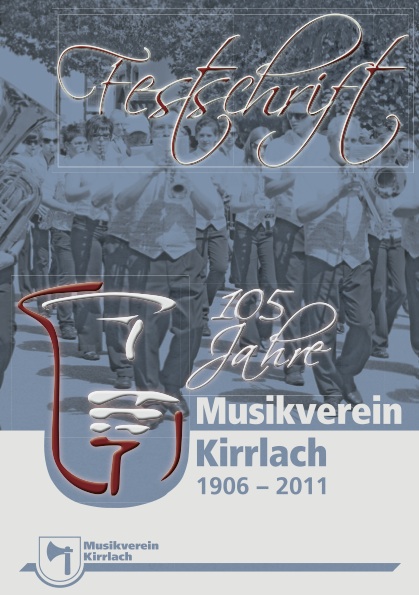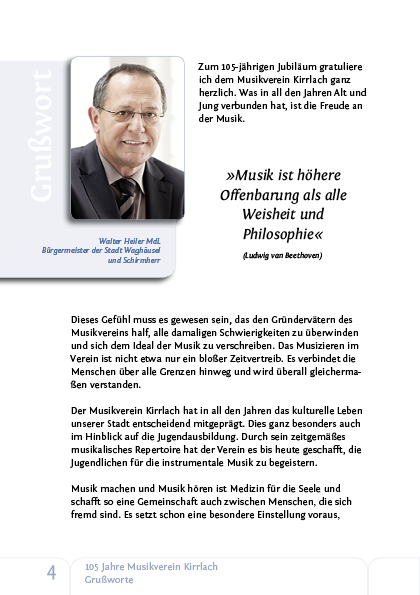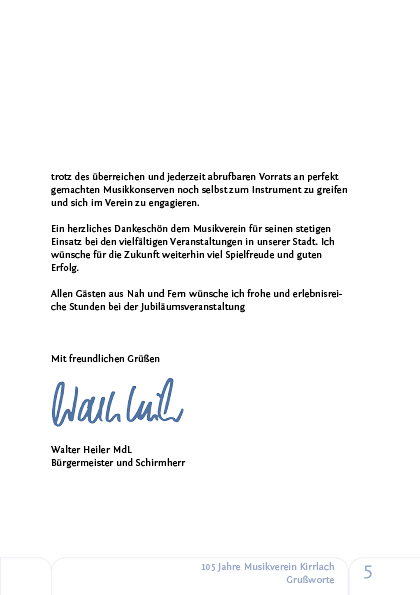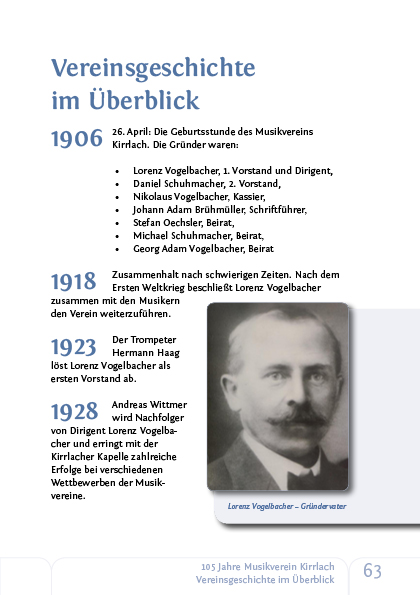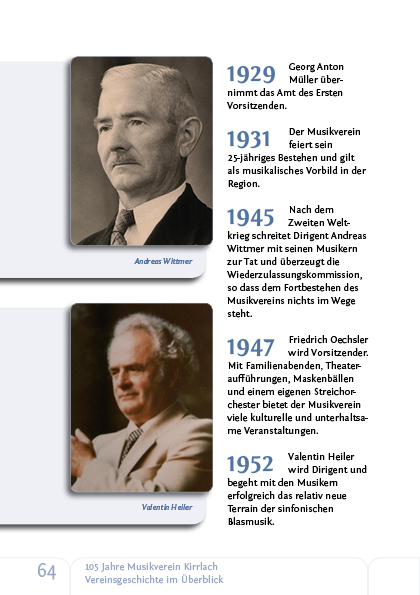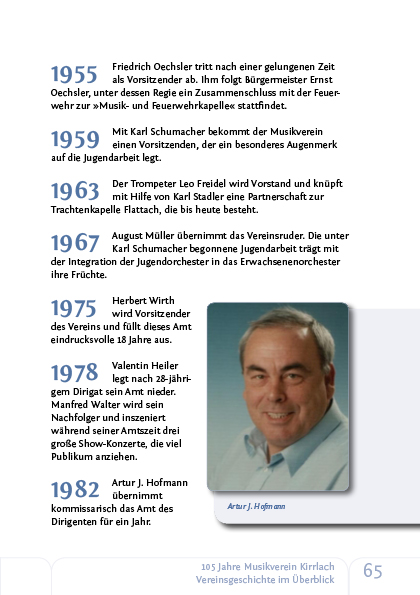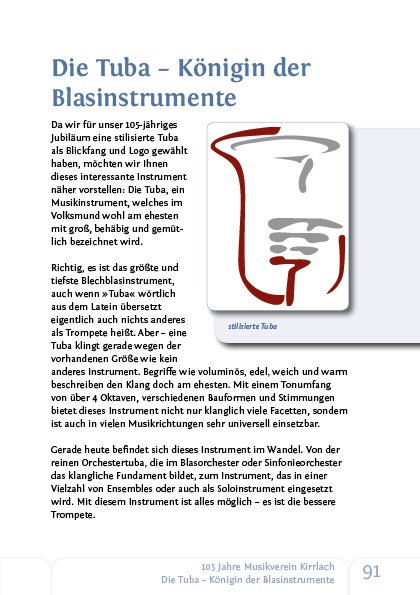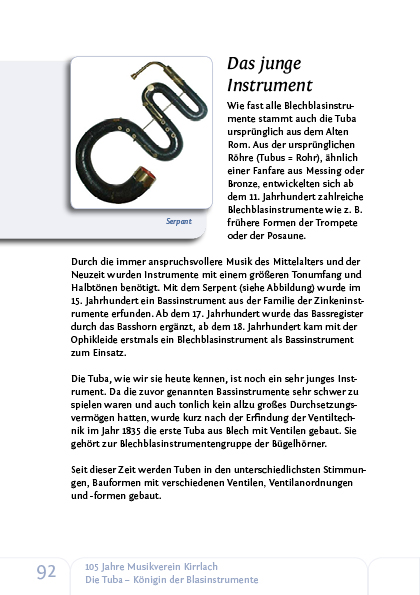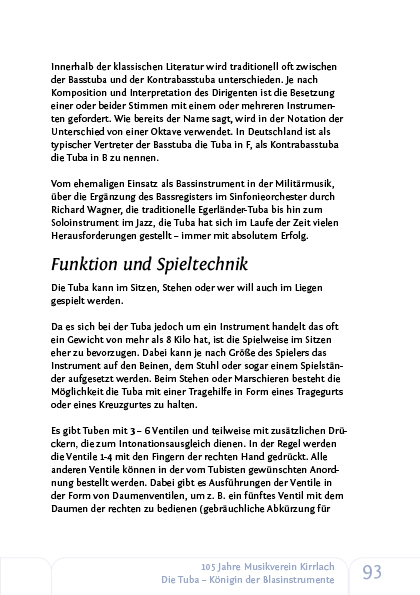
Satzspiegel und Schriftarten für Festschrift zum Vereinsjubiläum
Nachdem allgemeine Fragen der Detailtypografie weitgehend geklärt sind, bleibt nur noch zu bemerken, dass trotzdem das Gefühl aufkommt, es handelt sich hier um ein Sachbuch oder um eine kleinformatige Zeitschrift.
Eine Festschrift verlangt nach einer anderen Gestaltung des Layouts.
Alles sollte eher etwas weniger gedrängt und freier wirken.
Umflossene Bilder geben weder Bild noch Text genügend Freiraum. Auch ist zu hinterfragen ob hier Kolumnentitel nötig sind. Es handelt sich um keine Zeitschrift.
Weniger Elemente auf einer Seite lassen das Ganze großzügiger erscheinen.
Die Kombination Serifenlose als Titelschrift und Antiqua als Fließtext hat sich tausendfach bei Büchern, Dissertationen etc. bewährt, passt aber in diesem Fall nicht. Umgekehrt wäre besser. D. h. Antiqua (festlicher) als Titelschrift und Serifenlose als Fließtext.
Der Umgang mit Leerraum darf bei einer Festschrift großzügig gehandhabt werden. Dies betrifft den Satzspiegel (der kann ausgefallener sein), Zeilendurchschuss etc., auch wenn das Papierformat eher klein ist.
[...] bleibt nur noch zu bemerken, dass trotzdem das Gefühl aufkommt, es handelt sich hier um ein Sachbuch oder um eine kleinformatige Zeitschrift. [...]
Du bringst mein Unbehagen auf den Punkt.
...bleibt nur noch zu bemerken, dass trotzdem das Gefühl aufkommt, es handelt sich hier um ein Sachbuch oder um eine kleinformatige Zeitschrift.
Das kommt vielleicht daher, weil ich im richtigen Leben im IT-Bereich arbeite und vor dort klare Formen gewohnt bin. Zum Thema Typografie bin ich gekommen wie die Jungfrau zum Kind. Trotzdem fasziniert mich das Thema (sonst hätte ich ja nicht die Profis hier gefragt).
Ich werde nochmals in mich gehen.
Die Kombination Serifenlose als Titelschrift und Antiqua als Fließtext hat sich tausendfach bei Büchern, Dissertationen etc. bewährt, passt aber in diesem Fall nicht. Umgekehrt wäre besser. D. h. Antiqua (festlicher) als Titelschrift und Serifenlose als Fließtext.
Ok - probier ich aus.
Auch ist zu hinterfragen ob hier Kolumnentitel nötig sind. Es handelt sich um keine Zeitschrift.
Ok, es ist keine Zeitschrift. Ich dachte dabei an die verschiedenen Grußworte (Bürgermeister, Vorstand, etc.), die jeweils auf einer eigenen Seite stehen sollen - allerdings ohne Titelzeile.
Ich denke, dass dann ein Kolumnentitel ganz sinnvoll ist.
Eine Festschrift verlangt nach einer anderen Gestaltung des Layouts.
Ich bin ja der Ansicht, besser es ist gut gemacht und etwas steril als dieser kitschig bunte kram, den man überall sieht.
Aber ich denke mal das Problem wurde oben schon angesprochen, dass man wohl auch erst einmal die echten Texte abwarten muss. Dann kann man wahrscheinlich eher sehen, ob das ganze zu ›einfach‹ und unfestlich ist. Wenn dann nämlich die unterschiedlichsten Textarten eingearbeitet werden, kann das schon ganz anders aussehen. In so einer Festzeitschrift hat man ja nicht unbedingt seitenlangen Text sondern auch Interviews, Zeitpläne etc.
Andersrum könnte man aber auch über eine Hintergrundfarbe nachdenken, dann wirkt das nicht mehr so nüchtern. Und den vorgeschlagenen Schrifttausch würde ich auch ruhig mal ausprobieren ...
Eigentlich wollt ich heut Abend nochmal was dazu schreiben (hab grad Stress), aber Erwin hat es gut auf den Punkt gebracht :)
Überleg doch mal, die Serifenschrift für alles zu verwenden :)
Vielleicht komm ich heut Abend dazu, mal kurz was zu basteln, was ich mir so vorstellen würde, ohne viel über den Verein zu wissen – kann ich aber nicht versprechen :)
In so einer Festzeitschrift hat man ja nicht unbedingt seitenlangen Text sondern auch Interviews, Zeitpläne etc.
Genau so ist es.
Inhalte sind z. B.:
• Inhaltsverzeichnis
• Grußworte
• Festprogramm des Haupt-Festwochenendes (Freitag bis Montag)
• Vereinschronik (mit Bildern)
• Verwaltung, Dirigenten (aktuell und historisch)
• Bilder und Beschreibungen der verschiedenen Orchester
• Jugendausbildung
• Beitrittserklärung
• etc.
und natürlich Inserate, die das alles finanzieren ;-)
Vielleicht komm ich heut Abend dazu, mal kurz was zu basteln, was ich mir so vorstellen würde, ohne viel über den Verein zu wissen – kann ich aber nicht versprechen
Das wär natürlich toll - Danke für die Mühe!
Sitze zufälligerweise just in dieser schwarzen Morgenstund auch gerade an einer Chronik, noch zufälligerweise sogar auch "MV" -- wenn auch viel kleiner und vermutlich viel jünger...
Google zeigte mir diesen Thread, als ich nachschauen wollte, ob Werbeanzeigen eher auf geraden oder auf ungeraden Seiten erscheinen sollten -- so, dass sie möglichst unauffällig sind (dies dürfen natürlich die Anzeigenkunden nicht erfahren)...
Insgesamt ist es aber doch ein gutes Ergebnis für einen Laien. Wenn ich da an vergleichbare Veröffentlichungen aus meinem Heimatort denke …